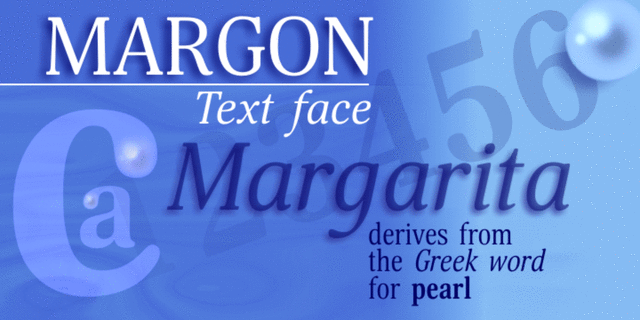
Шрифт Margon (Маргон) представляет собой переходную антикву строгого дизайна. Небольшие засечки, средний контраст, едва заметные скругления углов делают шрифт спокойным и уравновешенным. Шрифтовая семья Margon состоит из 18 начертаний, разбитых на 4 группы разных пропорций, имеющих индексы 360, 380, 400, 430. Значения индексов соответствуют показателям емкости набора в 28 кегле — самое широкое имеет емкость 3.6 знака на квадрат, самое узкое, соответственно, 4.3. Такой небольшой шаг по оси ширин дает возможность подобрать для каждого издания тот шрифт, который наилучшим образом соответствует требованиям экономичности и удобочитаемости, не прибегая при этом к искусственному искажению контура в программе верстки . Сферой применения шрифтов семейства Margon может быть книжный, журнальный и газетный дизайн. Шрифт разработан художником Натальей Васильевой. Выпущен компанией ПараТайп в 2012 году.
Текстовая пара c Calendula Light